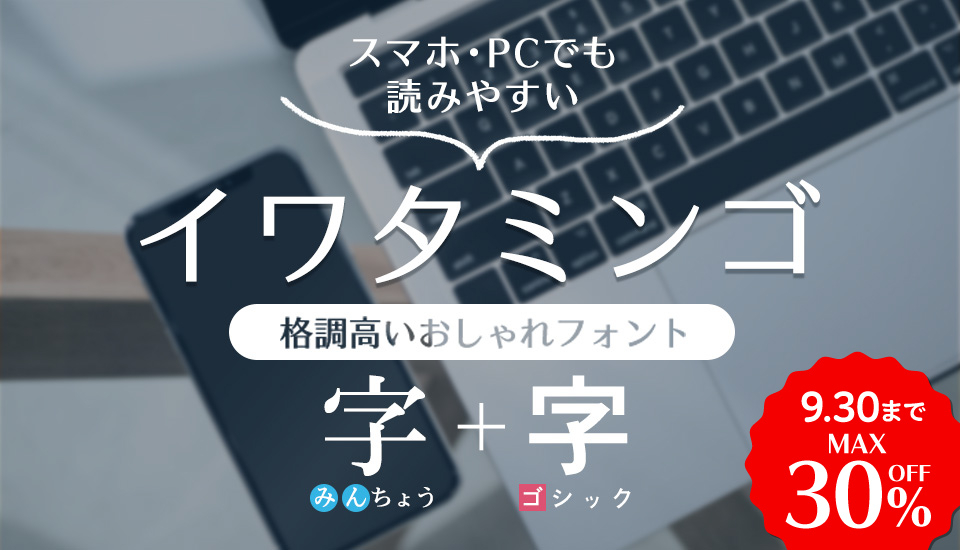
読みやすく洗練された視認性をもつ『イワタミンゴ』
2015年にグッドデザイン賞を受賞した「イワタミンゴ」は、明朝体とゴシック体の良いところを併せ持つおしゃれなフォントです。ミンゴのシャープで読みやすいデザインは、若者だけでなく、高齢者からも高い評価を得られました。
ディスプレイでの読みやすさを目的に開発されたイワタミンゴは、シャープでモダン。そしてスッキリと読みやすい。印刷から Web の世界まで、幅広くご利用いただけるフォントです。
デザイン性のあるUD書体 イワタミンゴ
イワタミンゴの誕生
昔からの明朝体やゴシック体を第一世代とすれば、2000年代に開発された年齢・性別や障害に関係なく、読みやすく、誤読されにくいUD(ユニバーサルデザイン)書体は第二世代。そして画面の解像度が日々上がっているスマートフォンなどのモニター、ディスプレイなどのデジタルメディアでの読みやすさを求めてデザインされた「イワタミンゴ」は第三世代といえる新しいフォントです。
その開発を手掛けたは橋本和夫氏。現在はイワタのデザイン部顧問で、1960年代から1990年代の約30年間にわたり写研のデザイナーとして多くの実績を残した書体デザイナーの重鎮です。橋本氏が展示会などに参加する中で、スマートフォンなどに使われているフォントに疑問を感じ、「電子媒体でももっと読みやすいフォントがあるのでは?」と思ったのがきっかけで開発されました。
UDフォントとしての機能と特徴
イワタミンゴはその名のイメージ通り、明朝独特のやわらかさとゴシック体の力強さを兼ね備え、またUDの視点も取り入れており、女性・若者の読者拡大を目指す新聞社からも注目を集める書体です。汎用性が高く、UDフォントとしての活用も期待でき、デジタルメディアで文字を読むこれからの時代のスタンダードとなりえる書体のひとつとして評価され、2015年度グッドデザイン賞を受賞しました。
イワタミンゴの特徴
明朝体のシャープさ・可読性の良さと、ゴシック体の強さ・整斉さを兼ね備えた、格調のある書体です。
文字のエレメントを単純化し、明るさとシャープさを表現しました。また、文字の横線を太くして横線との比率を少なくし、視認性の良い字形にしました。組版に普遍性を持たせ、同時に文字に格調ある雰囲気を持たせました。
高齢者にも優しい
イワタと静岡文化芸術大学、静岡新聞社の3者で行った新聞読者調査で、新聞の番組表に最適な書体として、高齢者の80%がミンゴを選択しました。理由は、ミンゴは行間がはっきり見えるので「読みやすい」と感じることでした。
ユニバーサルデザイン
おしゃれなだけでなく、ユニバーサルデザインでも優れたフォントです。その特性を生かし、自治体や公共施設のサインにも使用範囲が広がってきています。ディスプレイでの読みやすさを目的に開発されたイワタミンゴは、シャープでモダン。そしてスッキリと読みやすい。印刷からWebの世界まで、幅広くご利用できるフォントです。
イワタミンゴのラインナップ
M/D/B/E/Hの5ウェイトがラインナップされています。